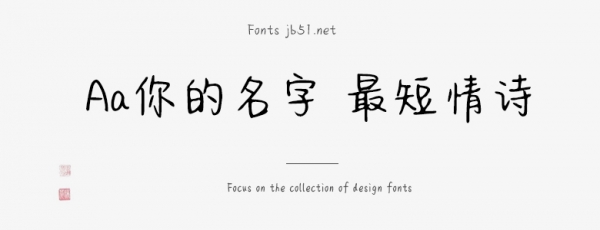
Aa你的名字 最短情詩是一款不錯(cuò)的藝術(shù)字體,由Aa字庫出品,字體筆觸適中,字形圓潤,擁有字符數(shù)22068和字形數(shù)22053,具有很好的視覺感,適合應(yīng)用于藝術(shù)設(shè)計(jì)、平面宣傳設(shè)計(jì)、網(wǎng)頁設(shè)計(jì),書法字帖等領(lǐng)域,需要的朋友可以前來本站下載。